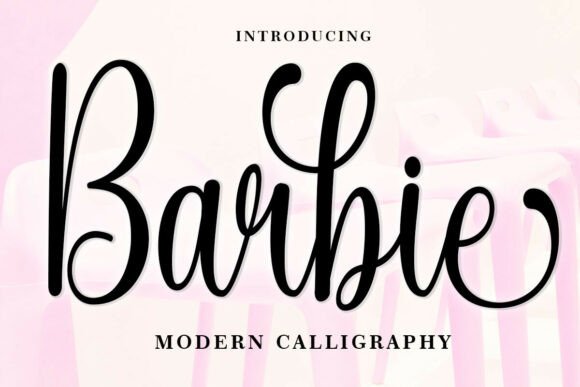
Barbie Script
قد يكون العثور على عناصر التصميم المناسبة أمرًا صعبًا، ولكن Barbie Script يقدم مجموعة استثنائية ترتقي بعملك على الفور.
سواء كنت تقوم بإنشاء منتجات الطباعة عند الطلب أو دعوات الزفاف أو رسومات وسائل التواصل الاجتماعي، فإن Barbie Script هو الخيار المثالي.